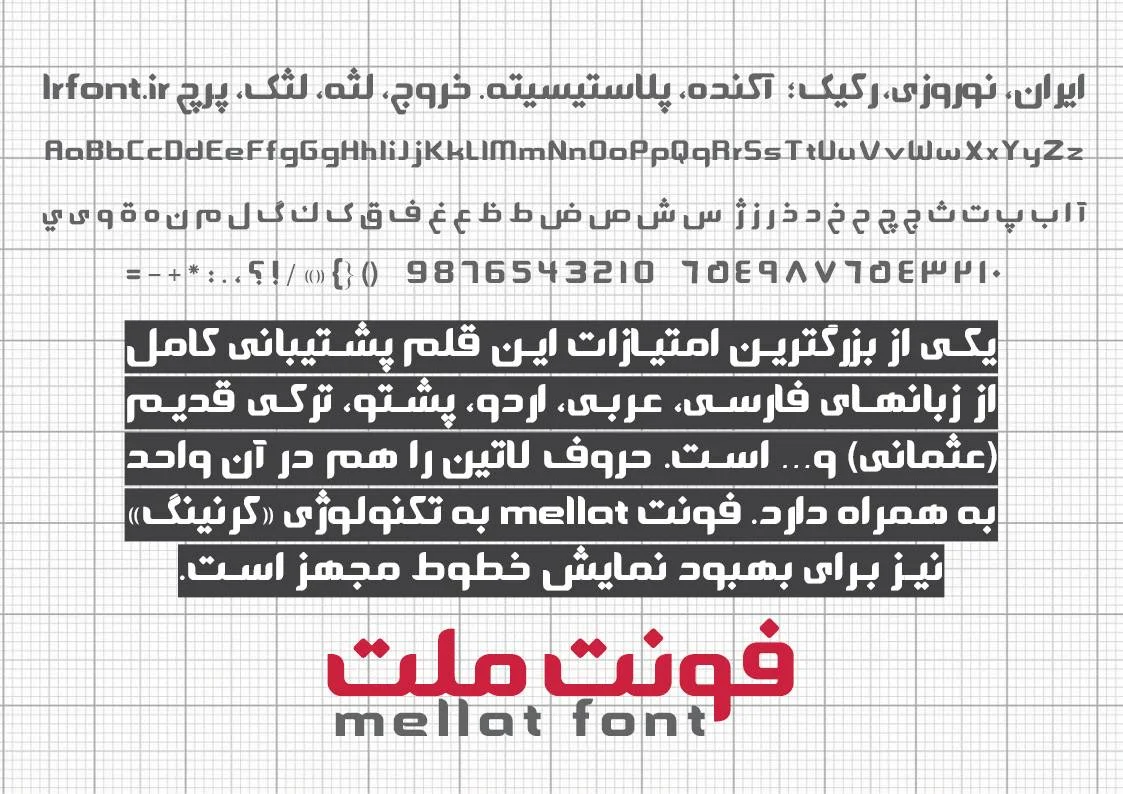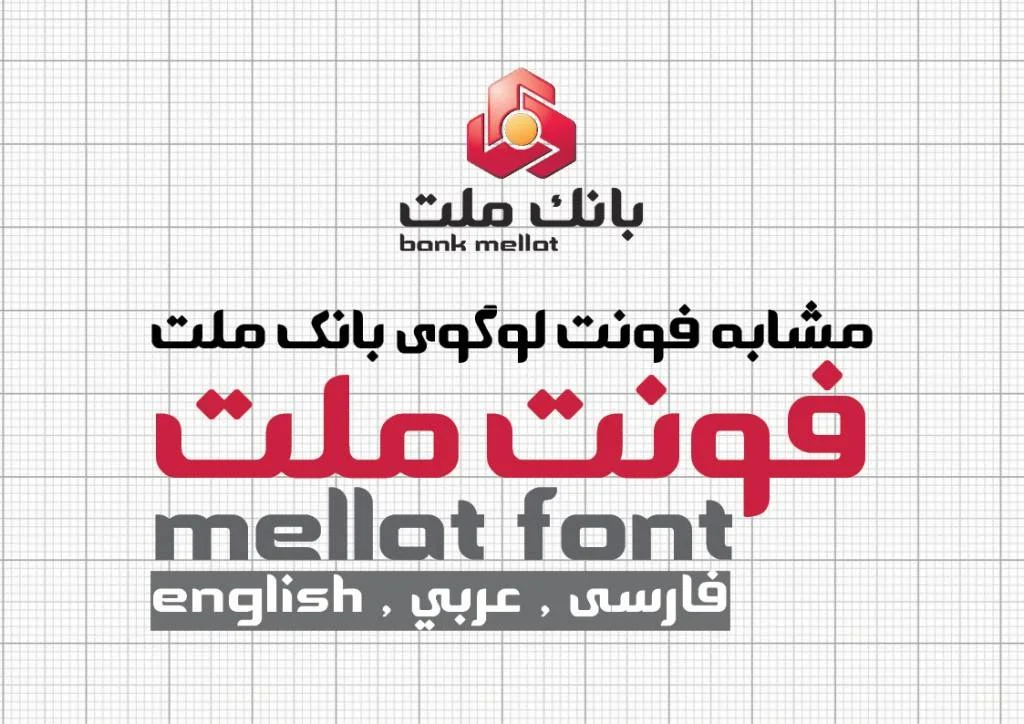
فونت بانک ملت
فونت ملت
فونت ملت را ایران فونت مفتخر است برای نخسیتن بار و به طور کاملا انحصاری منتشر کند.
دانلود فونت فارسی ملت ، تنها فونت واقعی مشابه با لوگوی بانک ملت
دانلود فونت فارسی ملت | فونتی جذاب و خوانا
گروه ایران فونت، فونت ملت را با الهام از لوگوی بانک ملت در سال ۱۳۹۳ و ۱۳۹۴ طراحی و پیاده سازی کرده است. این فونت کاملا open type ساپورت بوده و فرمت آن otf است. قابلیت آن را دارد که در تمام پلت فرم ها همچون لینوکس، مک، ویندوز، اندروید و همچنین وب به خوبی اجرا گردد. این فونت از تمام استانداردهای لازم برخوردار بوده و از زمستان ۹۴ جهت استفاده طراحان و گرافیست های حرفه ای عرضه گردید.
امتیازات فونت ملت
یکی از بزرگترین امتیازات این قلم پشتیبانی کامل از زبانهای فارسی، عربی، اردو، پشتو، ترکی قدیم (عثمانی) و… است. حروف لاتین را هم اندازه و کاملا مشابه حروف فارسی آن در خود به همراه دارد. فونت mellat به تکنولوژی «کرنینگ» نیز برای بهبود نمایش خطوط مجهز است. این فونت ضمن زیبایی بصری از خوانایی بسیار بالایی برخوردار است. به گونه ای که در فواصل دور هم قابل خواندن است. از دیگر کاربردهای این فونت می توان به استفاده از آن به عنوان تیتر و میان تیتر اشاره کرد. همچنین در سایت های می تواند برای عنوان ها و زیر عنوان ها استفاده گردد. فونت ملت قدرت آرامش دهنده بسیار بالایی دارد. بطوری که خواندن متن های نوشته با این فونت مخاطب را نسبت به نوشته اعتماد بالایی می دهد. فونت ملت فونتی بسیار روان، خوانا و آرامش بخش است و در تابلوها، پوسترها، وب، تلویزیون  و در هر طرحی که میخواهید در عین سنگین بودن جذاب و دوست داشتنی باشد قابل استفاده است. امیدوارم از تایپ با این فونت لذت ببرید (: